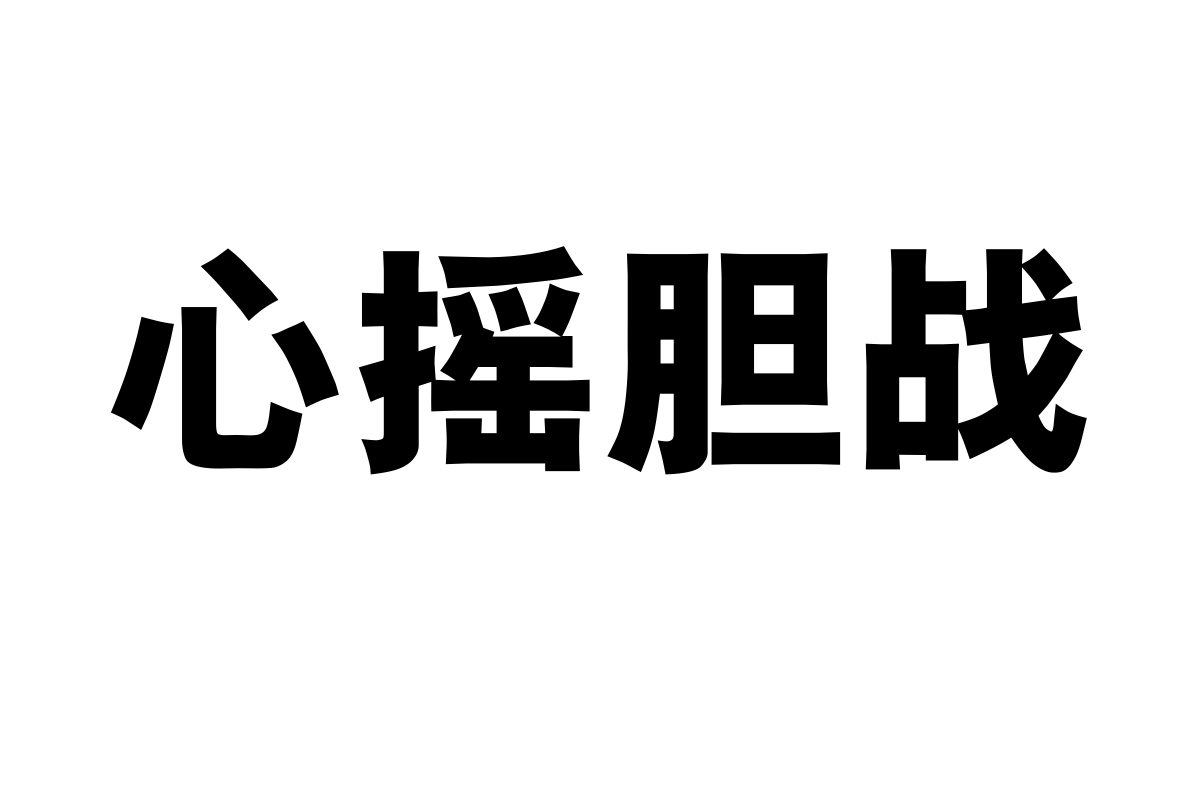
汉仪粗黑简是一款具有现代感和简洁风格的中文字体。它由汉仪字库出品,设计灵感来源于传统书法中的“黑体”字,但更注重线条的流畅性和结构的紧凑性。这款字体的特点是笔画粗细适中,字形结构均衡,给人一种清晰、易读的感觉。
在应用方面,汉仪粗黑简适用于需要强调文字清晰度和易读性的场合,如标题、正文等。它的使用可以提升整体的设计质感,使得文本更加醒目。此外,由于其简洁的设计风格,也适合用于一些简约风格的网页和界面设计。